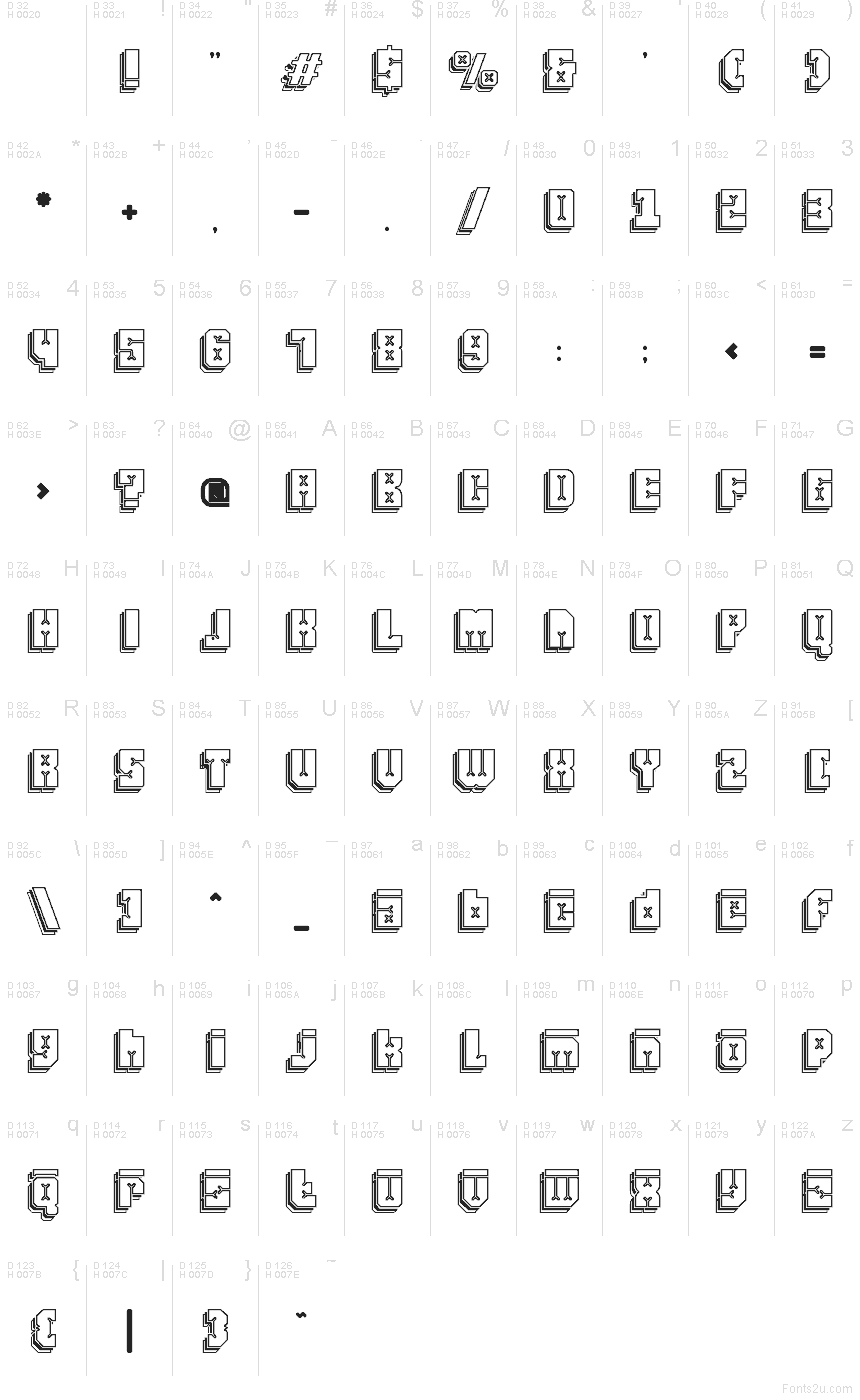
Friez Eleven od Putracetol Studio je bezplatné, groovové 3D titulkové písmo definované vysokými obdélníkovými rámečky a odsazenými obrysy, díky nimž každé písmeno vypadá jako krabicový nápis, který se lehce posunul ze své pozice. Toto opakující se orámování dodává designu pevný, plakátový rytmus, zatímco jednoduché vnitřní tahy brání tomu, aby písmo působilo příliš hutně.
Nejlépe vynikne na obalech alb, letácích k akcím, plakátových nadpisech, streetwearové grafice a titulních kartách na sociálních sítích, kde tato orámovaná silueta dokáže zaujmout na první pohled. Krabicová konstrukce navíc dodává krátkým popiskům na obalech nebo návrhům samolepek výrazný, vrstvený vzhled, který působí spíše jako grafický nápis než běžné titulkové písmo.
Friez Eleven